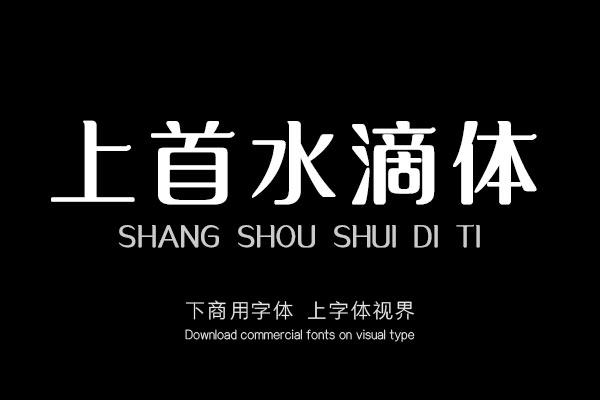
上首水滴体,字体转角圆润,笔端圆滑似水滴,疏密有致,稳重不失俏皮。适用于搭配标志、广告标语、商业广告等高端属性。购买须知:“下载服务费”与“字体VIP”所获得字体 仅用于个人非商用, 商用请联系付费授权。本字体为电脑用字,手机没有root权限不支持直接手机换字(手机如何root,请自行百度搜索教程)。购买前请先 了解清楚后再付款 ,字体为虚拟产品无法回收 一旦购买不支持退款。